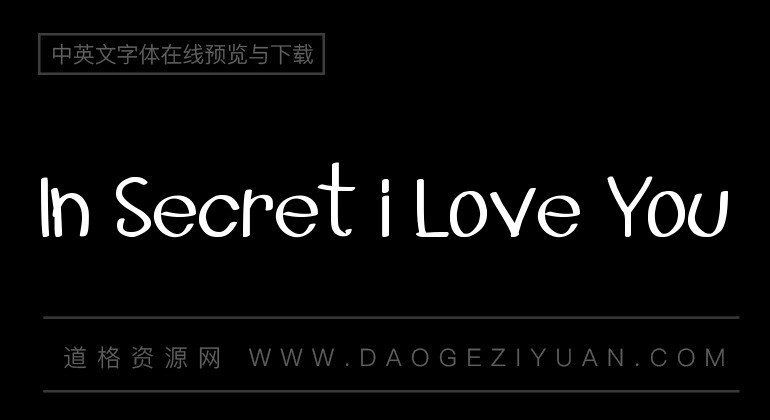
"In Secret I Love You" 是一种手写风格的字体,具有温暖、亲密和个人化的感觉。它由字母、数字和标点符号组成,每个字符都呈现出一种自然、流畅的笔画,有些字符的笔画甚至有点模糊,仿佛是手写的效果一样。 "In Secret I Love You" 字体的特点在于它的字母之间距离比较接近,这样可以给人一种亲密、紧密的感觉。此外,字母的大小不完全一致,这也增加了字体的个性化特点。总的来说, "In Secret I Love You" 是一种非常适合用于表达个人情感、强调某些信息或添加一些温馨氛围的字体。内容介绍
In Secret i Love You是一款非常不错的手写艺术字体,具有很好的视觉感,适合于文化类的宣传设计、商业类品牌的广告和产品包装设计以及个性化文字排版等较多场景。